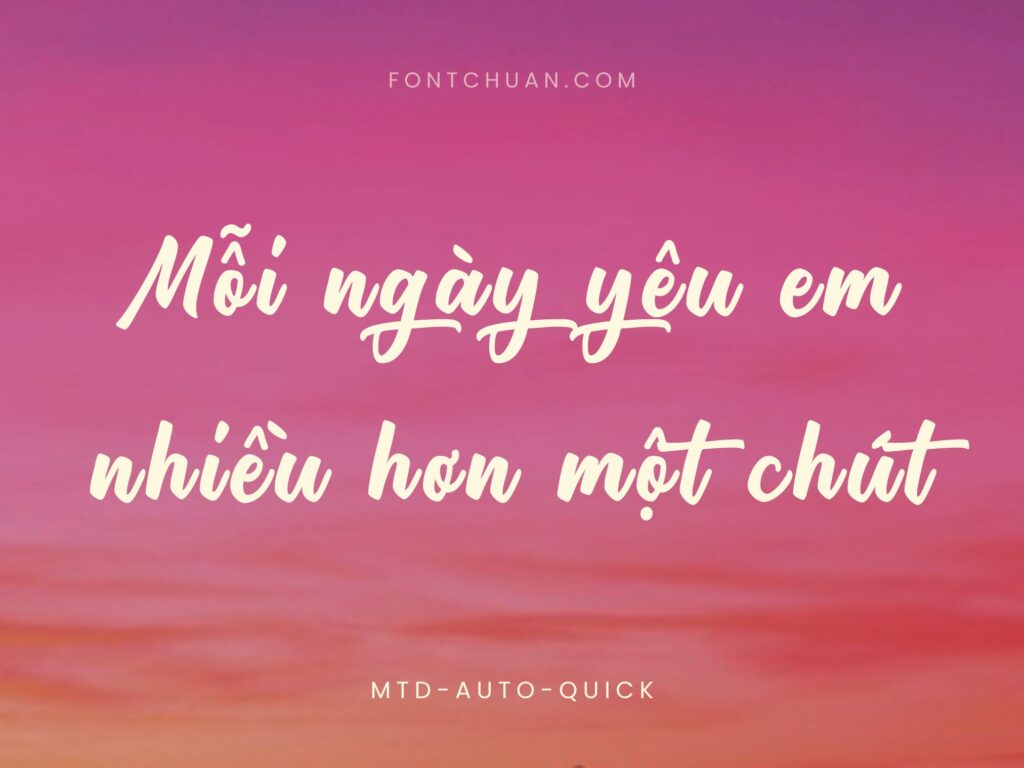
Font Auto Quick là một kiểu chữ mang phong cách mạnh mẽ và hiện đại, được thiết kế để sử dụng trong các thiết kế liên quan đến công nghệ, tốc độ và động cơ. Với các đường nét sắc sảo và bố cục cân đối, Auto Quick mang đến sự mạnh mẽ và chuyên nghiệp cho các dự án sáng tạo.
Phiên bản Auto Quick đã được Việt hóa bởi Mộc Hạ, hỗ trợ đầy đủ tiếng Việt cùng hơn 64 ngôn ngữ khác như Anh, Pháp, Tây Ban Nha, Đức và Ý, mở rộng khả năng ứng dụng trong thiết kế đa ngôn ngữ. Font này đã được thành viên Font Chuẩn sưu tầm và chia sẻ, đáp ứng nhu cầu của cộng đồng thiết kế. Với thiết kế đậm chất công nghiệp, Auto Quick phù hợp cho các ứng dụng như thiết kế logo, tiêu đề, bảng hiệu, bao bì sản phẩm và các ấn phẩm quảng cáo. Các ngành nghề như quảng cáo, giáo dục, công nghệ và ẩm thực có thể tận dụng font này để tạo ra thiết kế ấn tượng và thu hút.